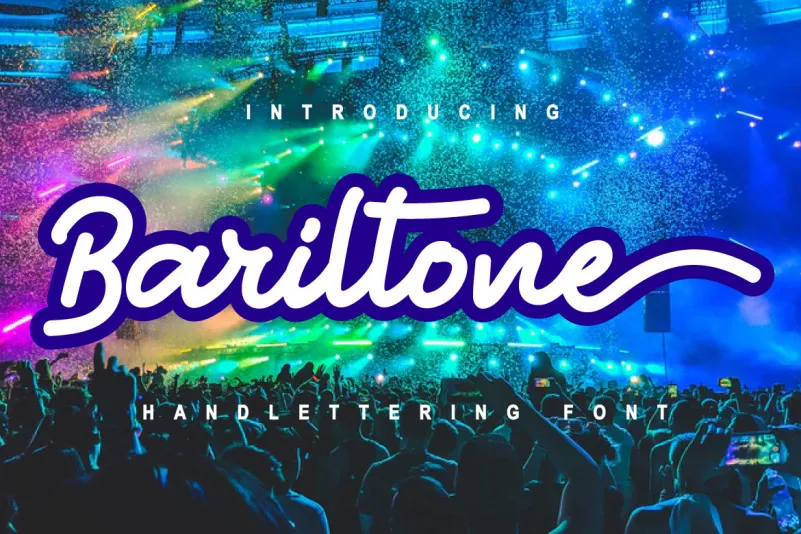
Beriltone Font – Fonte Grátis
Beriltone Font
Esta é uma fonte para escrita cursiva que transmite um toque elegante. É perfeita para seus projetos favoritos, seja para criar cartões de casamento com estilos belamente elaborados, arte de papel decorativo de alta qualidade, postagens sociais atraentes ou qualquer outra coisa que você possa imaginar. Suas características cíferas delicadas e textura elegante tornam este design uma escolha perfeita para quem deseja adicionar um toque único aos seus trabalhos, seja em cartões de aniversário, folders de viagem ou até mesmo gráficos empresariais.
Designer: makaryo